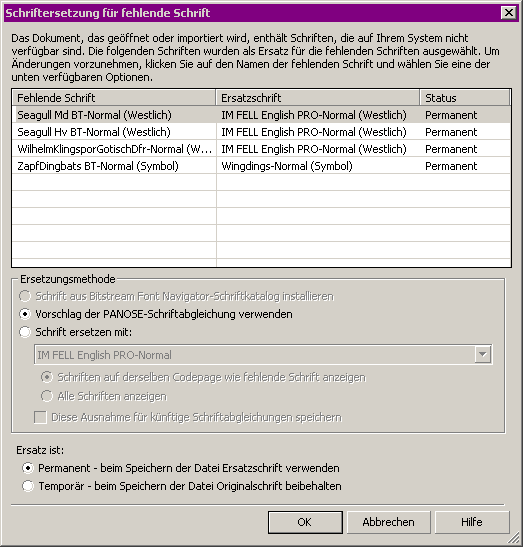
Unterschiede im Schriftbild bei MS Word & LibreOffice
Ich bin beim Durchlesen meiner PDFs auf einige Unterschiede gestoßen, auch wenn beide PDF-Dokumente mit identischer Schriftart (Minion Pro 12pt) geschrieben wurden. Der einzige Unterschied ist, dass Version 1 durch LibreOffice unter MacOS entstanden ist und Version 2 durch Word 2013 (unter Bootcamp-Windows).
Leider kenne ich mich mit solchen Fragen überhaupt nicht aus und konnte auch im Internet keine Informationen über dieses Phänomen finden. Ich hoffe, dass ich hier eine Antwort finde!
Grundsätzlich schätze ich MS Word 2013, da ich mich eingewöhnt habe und sehr gut zurecht komme. Allerdings finde ich das Aussehen der Schriftart in LibreOffice wesentlich angenehmer...
Was ist der Grund für solche Unterschiede? Kann man Word 2013 angleichen?
LibreOffice (links) und MS Word 2013 (rechts) mit einigen Unterschieden...
Das sind nihct nur Unterschiede in der Darstellung der Minion Pro, sondern es ist eine ganz andere Schrift, die da von Word verwendet wird,
die rechte Schrift ist Apple Times Bold.
Sehr wahrscheinlich eine Panose-Ersetzung, weil die Minion Pro nicht auch im Bootcamp-Windows installiert ist.
Vielen Dank für die schnellen Antworten, ich habe gerade noch einmal nachgesehen und festgestellt, dass zwar "Minion Pro" als Schriftart angezeigt wird (Word), dieser aber unter Windows überhaupt nicht vorhanden ist.
Sie wurde daher vermutlich, wie oben schon beschrieben, mit einer anderen Schrift ersetzt, das hätte ich vorher kontrollieren sollen...
Eines der bekannten netten Features von Word.
Libre Office zeigt in Version 4.0.3.3 unter WIN übrigens exakt das gleiche Verhalten, grad getestet. Das Problem ist mutmaßlich in erster Linie nicht Word, den Konflikt dürften viele Programme genauso lösen, wenn sie beauftragt werden, ein Dokument zu öffnen, das Schriften verwendet, die unter dem Host-System nicht bereitgestellt sind. Himmel, möcht ich dich hören, wenn WORD sich in der Situation weigern würde, das Dokument mit einer Ersatzschrift anzuzeigen. Oder wenn es moniert, dass irgendeine falsche ARIAL-Version auf dem Zielsystem vorhanden ist.
Nun, dieses Verfahren der Panose-Ersetzung ist ja durchaus sinnvoll. Die Fonts dürfen ja i.d.R. nicht in eine offene Datei eingebunden werden, daher versucht dann die Software aus dem anderen Recher einen Font zu finden, der dem eigentlich beabsichtigten so nahe wie irgend möglich kommt, um so ein nicht all zu sehr auseinandergefallenes Bild zu liefern, oder gar unlesbartes Zeug.
Schön wäre zwar, wen das Programm beim Öffnen einer Datei die fehlenden Schriften anzeigen würde, aber ich befürchte, das würde das Gros der Nutzer nur noch mehr verunsichern.
Nun in CorelDraw geht es doch auch. Es wird eine Ersatzschrift vorgeschlagen, man kann aber auch eine andere wählen und noch bestimmen ob die Änderung nur für diese Sitzung oder dauerhaft vorgenommen werden soll.
Möglicherweise würde dies einige Nutzer irritieren und zum rasch mal ins Dokument gucken wäre es bisweilen nervig. Aber man könnte den Dialog ja standardmäßig weglassen und in den Optionen einschalten. So wäre doch allen geholfen.
... wobei nicht alle gezeigten Unterschiede auf den fehlenden Font zurückzuführen sind.
Ich entdecke linkerhand mindestens noch eine fi-Ligatur. Könnte Word das auch schon automagisch?
Diese Corel-Funktion hat mir schon oft geholfen. Allerdings ist der Button, denn ich dann drücke, in den meisten Fällen der Abbrechen-Knopf, um so schnell erst die nötigen Schriften zu installieren. Als verbesserung wünschte ich mir einen Button: „Fehlende Schriften suchen und installieren„ wo man dann den Pfad zum Speicherort seiner Schriftensammlung eingibt, und das Programm sucht dort die fehlende Schriftart, installiert sie und öffnet dann das Dukument.
Aber gut, träumen darf man ja...
Word kann das, wenn Du es anschaltest. Defaultmäßig ist das deaktiviert. Wobei afair die Ligaturen in OSX deren Renderer Quartz geschuldet sind, die WPF unter Windows kann das zwar auch, macht es aber nicht einfach.